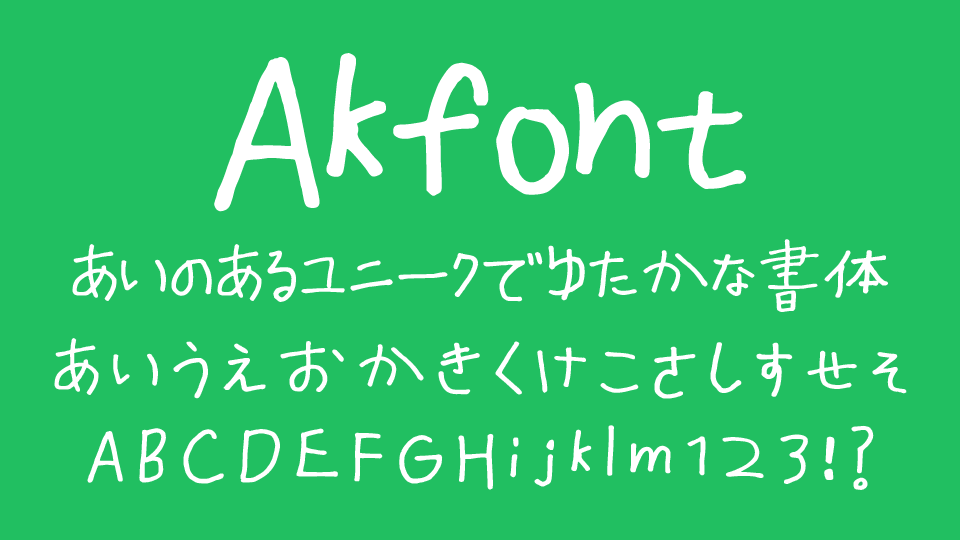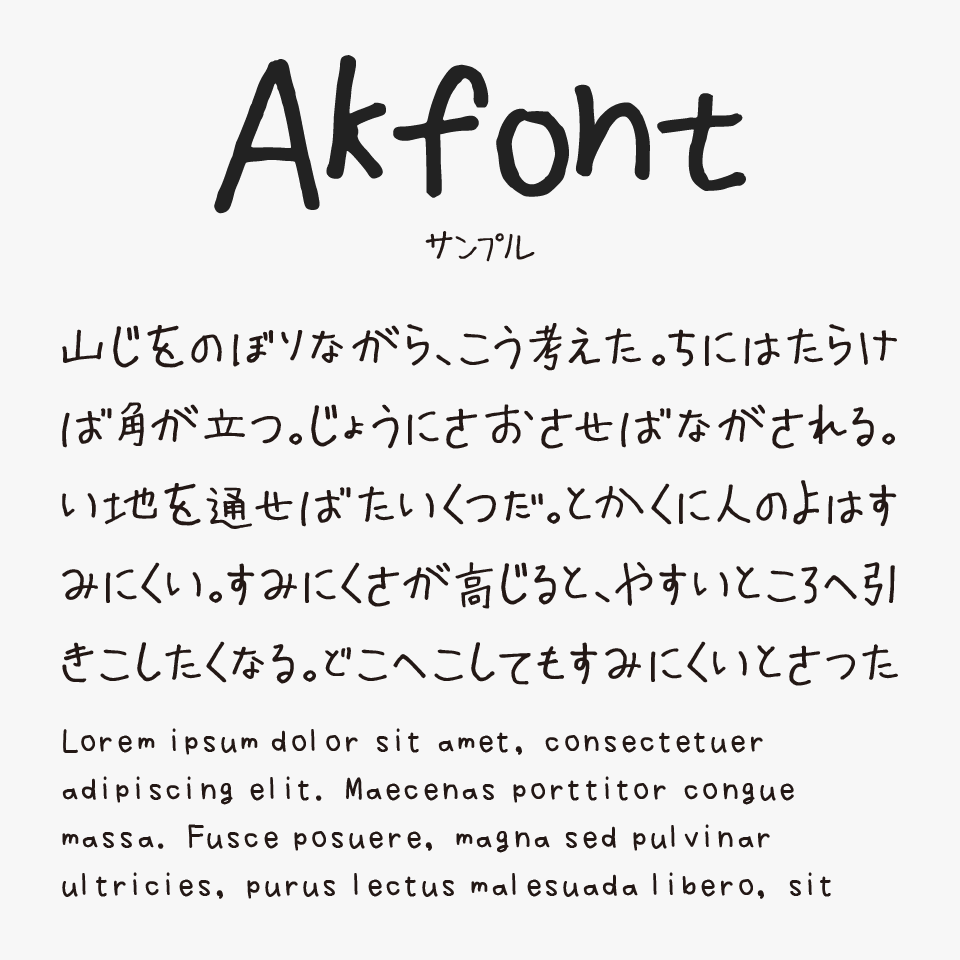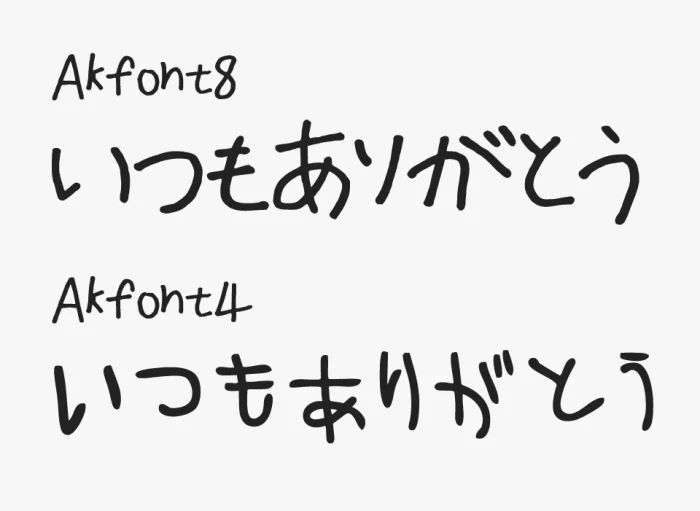
Akfont/Mafontは、実際の4歳・5歳・8歳の子供が書いた自然体の線がとっても可愛らしい手書きフォントです。
少し揺らぎのある文字のバランスが、いい意味でラフな空気感を生み出しているフォントです。肩の力が抜けたような子どもっぽさがあり、素朴で親しみやすい雰囲気を自然に演出してくれるフォントです。
Akfont / Mafont
Akfont4(4歳)/Akfont8(8歳)/Mafont5(5歳)の3スタイル用意されており、年代ごとの文字トーンが違って、またかわいいですね。